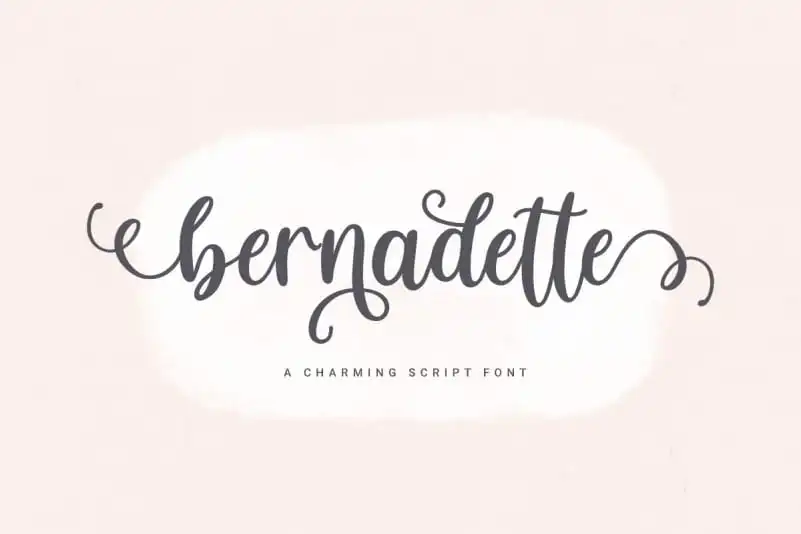
Bernadette Calligraphy Font – Download Grátis
A Bernadette Calligraphy Font é uma elegante escolha para estilos leves e delicados. Com traços acentuados nas extremidades, ascenderes e descendentes suaves, esta fonte script apresenta um charme único que se encaixa perfeitamente em diversas aplicações. Ideal para criação de identidade visual feminina, o uso desta fonte é uma escolha inteligente para marcas do gênero, cartas personalizadas ou projetos de bordados. A Bernadette também destaca-se como uma fonte versátil que se adapta perfeitamente a logotipos, selos, mensagens de celebridades e outros materiais digitais modernos como redes sociais e websites. A sua utilização é tanto para o seu projeto criativo atual como um futuro recurso indispensável para qualquer designer gráfico em busca de uma fonte única e delicada.